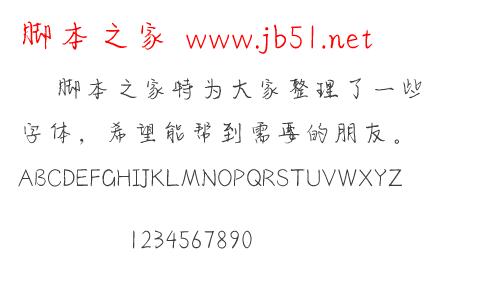
曲終人不散字體是一款非常好看的中文字體,同時也是由文道字庫傾情發(fā)布的作品,字體字型的排序十分整潔,有序,筆畫婉轉(zhuǎn)清麗,整體的效果非常出色,適應(yīng)于報紙和雜志和書籍中常用字體海報、個性促進(jìn)品牌標(biāo)志設(shè)計、字體設(shè)計、文本裝潢、信息展示、篆刻制模英文、數(shù)據(jù)制作、裝潢設(shè)計、視覺設(shè)計、字帖等一切合法應(yīng)用場景,有喜歡的朋友可免費(fèi)下載收藏。